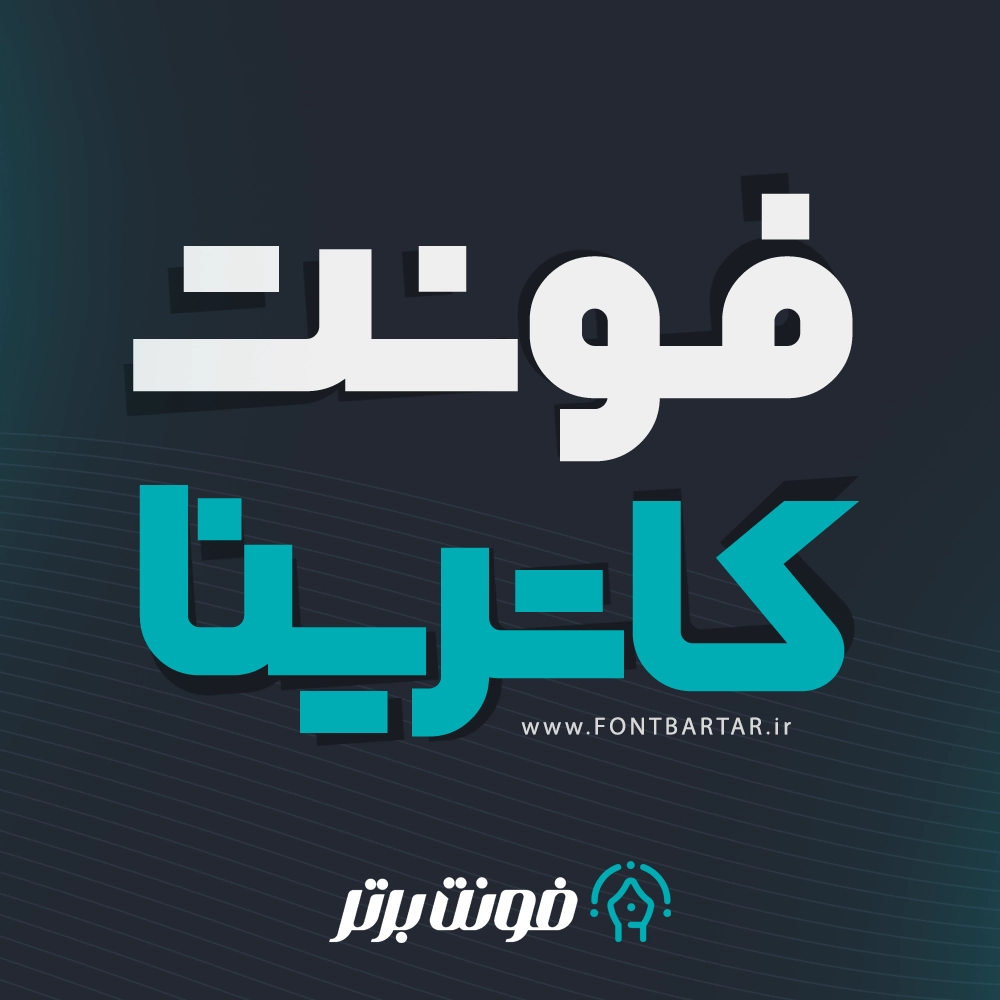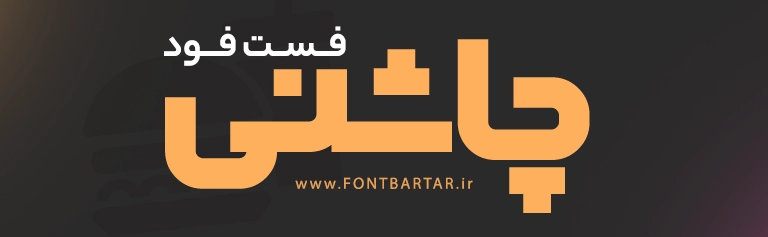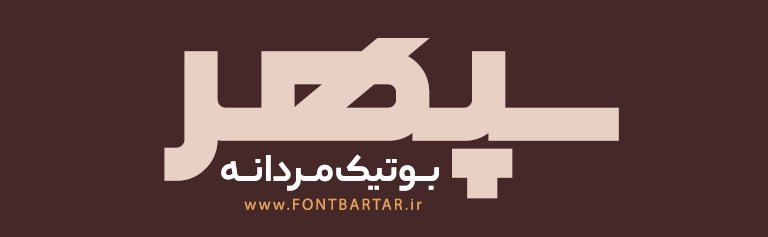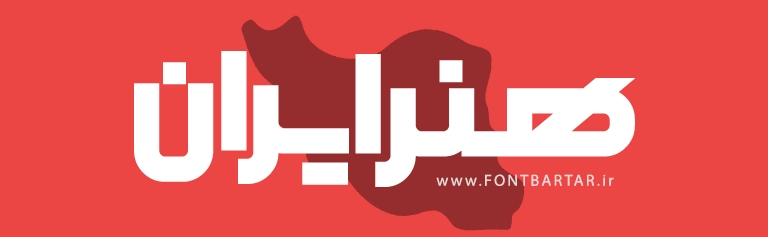
دانلود فونت کاترینا | فونت فارسی جذاب و مدرن
دانلود فونت فارسی کاترینا یک فونت فارسی جذاب، مدرن و چشمنواز است که با ساختاری قدرتمند و فرمهای هندسی منظم طراحی شده است. دانلود فونت برای طراحانی که به دنبال ایجاد نوشتههایی تاثیرگذار، خوانا و حرفهای هستند، انتخابی ایدهآل محسوب میشود. ترکیب ضخامت مناسب حروف و طراحی امروزی باعث شده فونت کاترینا در نگاه اول توجه مخاطب را جلب کرده و پیام را بهصورت واضح منتقل کند.
ویژگیهای برجسته فونت زیبا فارسی کاترینا
فونت زیبا فارسی با در نظر گرفتن نیاز طراحان گرافیک و تولیدکنندگان محتوا طراحی شده و از نظر بصری و فنی عملکرد بسیار بالایی دارد.
مهمترین ویژگیها:
- طراحی مدرن و حرفهای
- خوانایی بالا در سایزهای مختلف
- مناسب تایپوگرافی فارسی
- هماهنگ با طراحی دیجیتال و چاپ
- ایدهآل برای عناوین و تیترهای تبلیغاتی
کاربردهای فونت فارسی جذاب در طراحی
فونت فارسی کاترینا انتخابی عالی برای پروژههای متنوع گرافیکی است، از جمله:
- طراحی پوستر تبلیغاتی
- بنرهای دیجیتال و چاپی
- فونت زیبا برای استوری
- کاور پست و استوری اینستاگرام
- طراحی لوگوتایپ فارسی
- تیتر صفحات وب و لندینگ پیج
- محتوای تبلیغاتی و برندینگ
چرا خرید فونت زیبا کاترینا برای طراحی تبلیغاتی مناسب است؟
فونتهای تبلیغاتی باید در عین زیبایی، پیام را سریع و واضح منتقل کنند. فونت کاترینا با فرمهای قوی و ساختار استاندارد، باعث افزایش نرخ تعامل مخاطب شده و برای استفاده در کمپینهای تبلیغاتی دیجیتال و چاپی بسیار موثر است.
1. فونت کاترینا بیشتر برای چه نوع طراحی مناسب است؟
این فونت برای طراحی پوستر، بنر، تایپوگرافی و محتوای تبلیغاتی بسیار مناسب است.
2. آیا فونت کاترینا برای اینستاگرام کاربردی است؟
بله، به دلیل خوانایی بالا و ظاهر جذاب، برای پست و استوری اینستاگرام ایدهآل است.